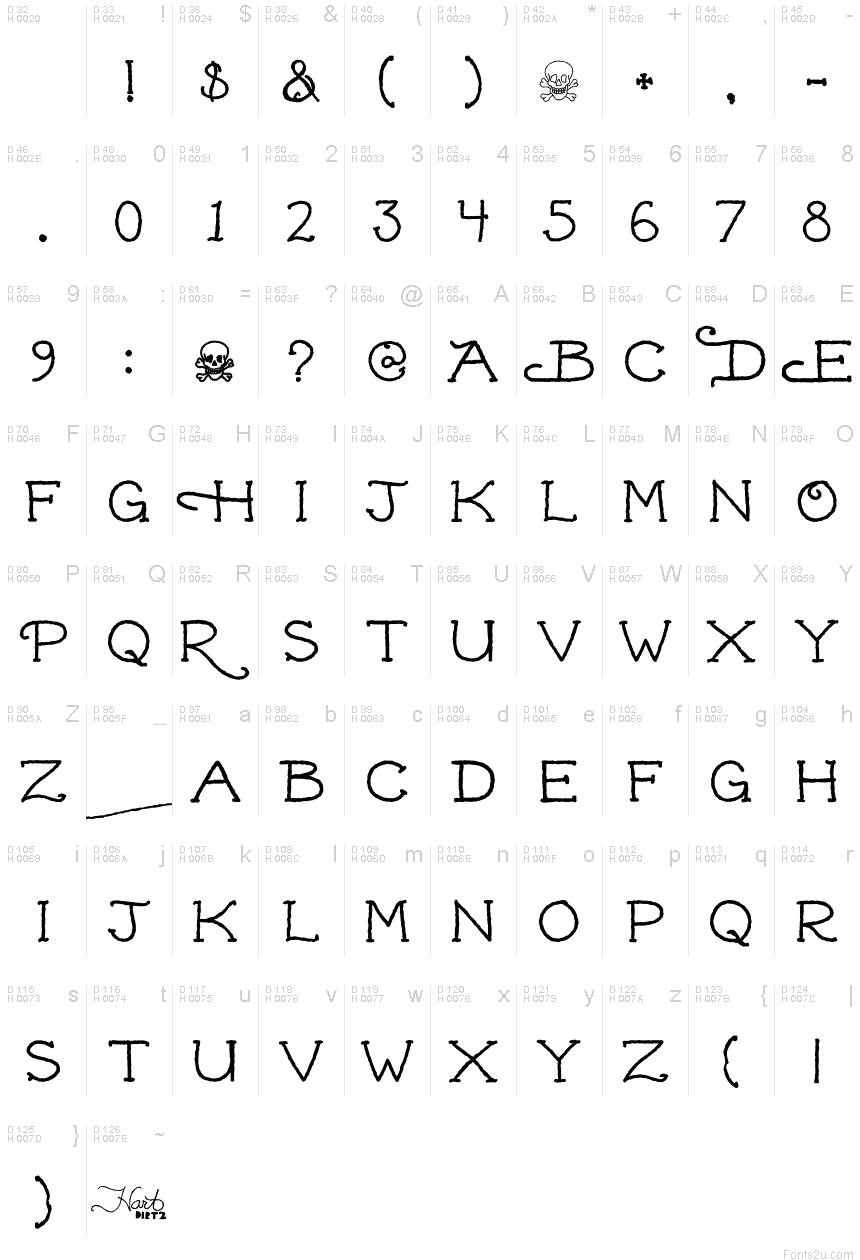
Dead Hardy od Dirt2.com to darmowy, surowy font pisany ręcznie, składający się z samych wielkich liter i utrzymany w klimacie horroru. Litery sprawiają wrażenie wyciągniętych i nierównych, z drżącymi kreskami, nagłymi haczykami i rozciągniętymi poprzeczkami, co nadaje całości niespokojny, „podrapany” rytm.
Świetnie pasuje do plakatów, okładek zinów, grafik zespołów garażowych, kart tytułowych i ulotek na Halloween, zwłaszcza tam, gdzie krótkie napisy potrzebują surowego, ludzkiego charakteru zamiast sterylnych liter. Jako darmowy font sprawdza się też w wyrazistych cytatach czy monogramach, ponieważ duże litery mają w sobie wystarczająco dużo napięcia i chwiejności, by przyciągać wzrok samodzielnie.